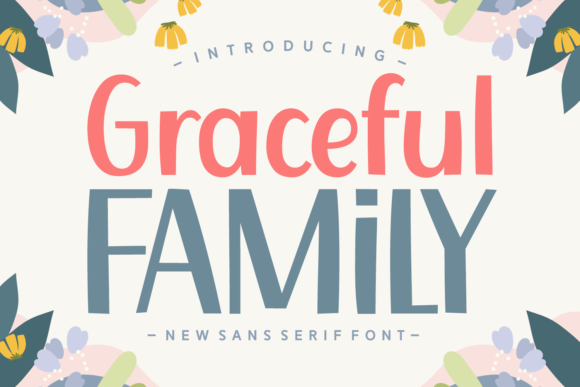
Graceful Family
إذا كنت تبحث عن أصول عالية الجودة مثل Graceful Family، فإن هذه الحزمة المميزة هي خيار رائع لمشاريعك الإبداعية.
سواء كنت تقوم بإنشاء منتجات الطباعة عند الطلب أو دعوات الزفاف أو رسومات وسائل التواصل الاجتماعي، فإن Graceful Family هو الخيار المثالي.